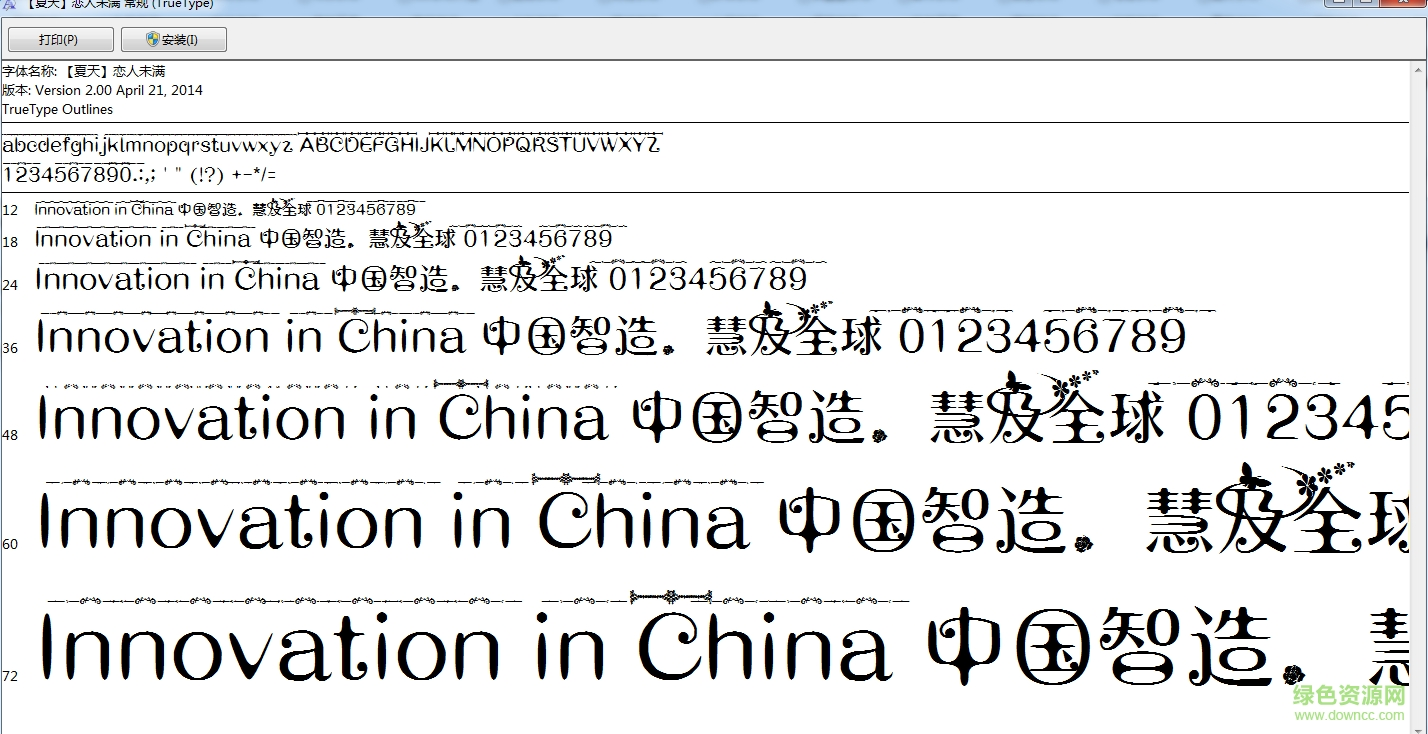
软件介绍 软件标签: 恋人未满字体 字体 恋人未满字体是一款感情抒发的字体,字形紧迫又好似神离,字体走位好似友达以上,恋人未满,或许字体也是有感情的,靠的太近容易看不清!有兴趣的朋友就来绿色资源网下载吧。恋人未满体字体安装方法第一种1.下载字体并解压缩;2.把文件根目录下的字体压缩包解压缩;3.把文件根目录下的安装字体.bat放到含有字体文件的文件夹中,双击安装字体.bat软件;4.文字添加完成第二种1.下载字体并解压缩;2.开始中打开控制面板;3.在控制面板中打开字体文件夹;4.把下载的字体复制到此文件夹下;5.文字添加完成小编点评这是一款众多用户都需要的经典字体,能够为你带来意想不到的效果,为你的作品增添更多光彩! 软件截图 上一张下一张(1 / 1) 安装详细截图 其他版本下载 标题 大小 更新日期 下载 下载地址 电脑版 恋人未满体字体 点击报错 软件无法下载或下载后无法使用,请点击报错,谢谢! 关闭报错反馈 请描述您所遇到的错误,我们将尽快予以修正,谢谢! *必填项,请输入内容 本类最新 dreamweaver字体库 首尔南山体字体 v1.06 官方版 潮字社风云简ttf 潮字社凌渡鲲鹏简体字体 潮字社曾玉波手书简字体 微博慧心字体 相关文章 Photoshop字体安装使用方法和技巧 如何解决“无法新增字体”问题 Win 7系统安装字体方法 网页字体大小设置方法 怎么改网页字体大小 在Linux系统中安装字体的几种方法 windows7字体显示问题:打开某些程序的时候显示的是乱码 用户评论 热门评论 最新评论 发表评论 查看所有评论(0) 昵称: 请不要评论无意义或脏话,我们所有评论会有人工审核. 字数: 0/500 (您的评论需要经过审核才能显示)